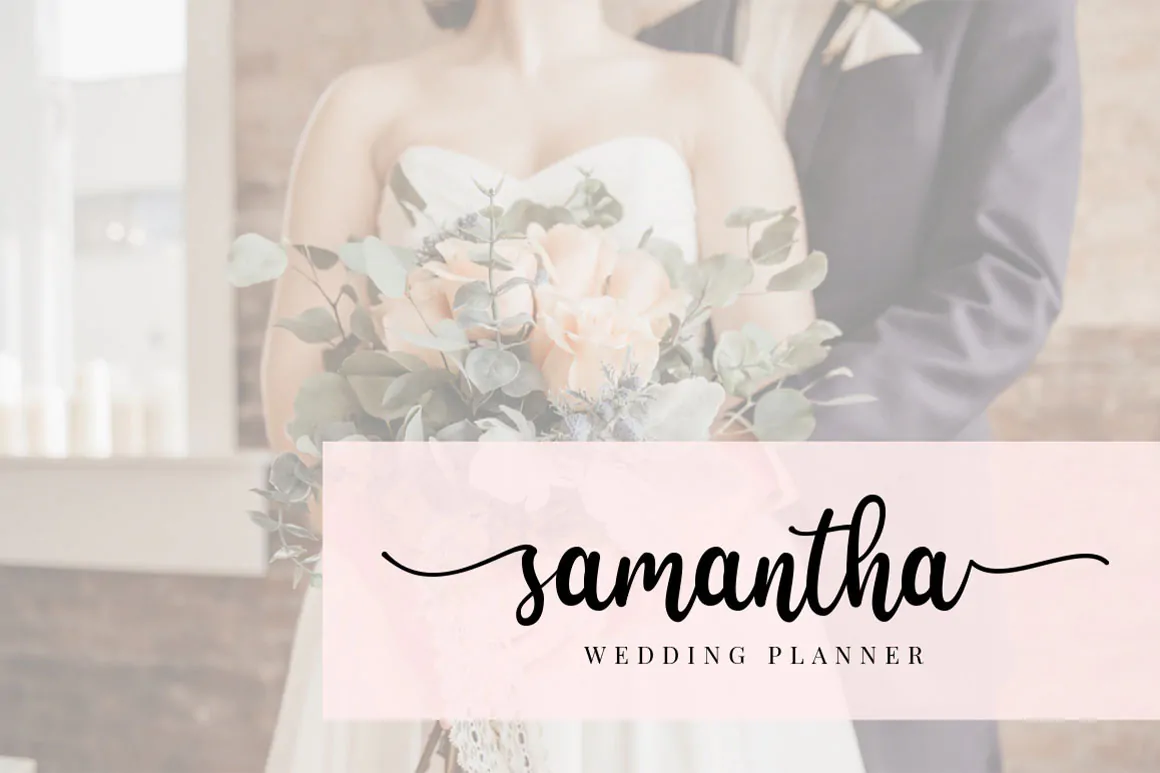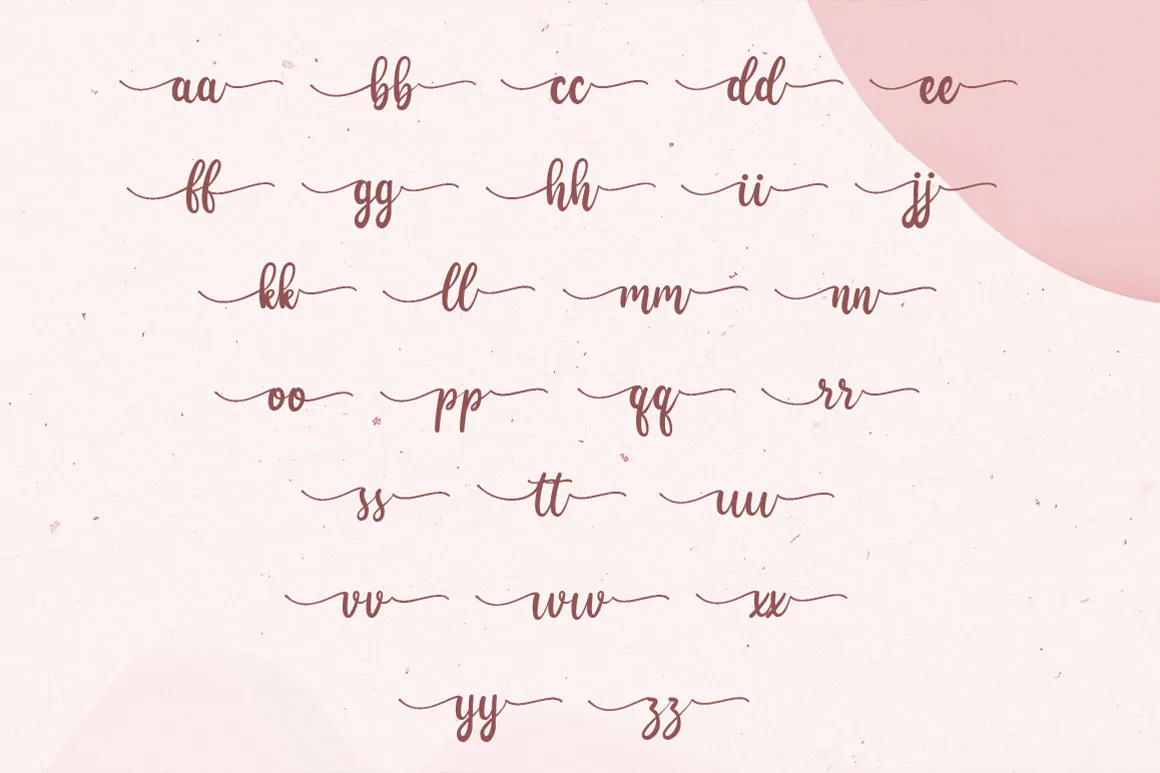
فونت رمانتیک و عاشقانه Dear Heart
فونت رمانتیک و عاشقانه انگلیسی
فونت رمانتیک و عاشقانه Dear Heart یک اسکریپت فونت دستنویس است که مناسب برای استفاده در طراحی انواع کارت تبریک، کارت عروسی، پوستر، کارت ویزیت، بسته بندی محصولات و … میباشد.